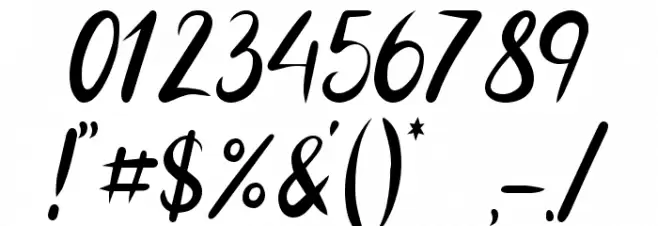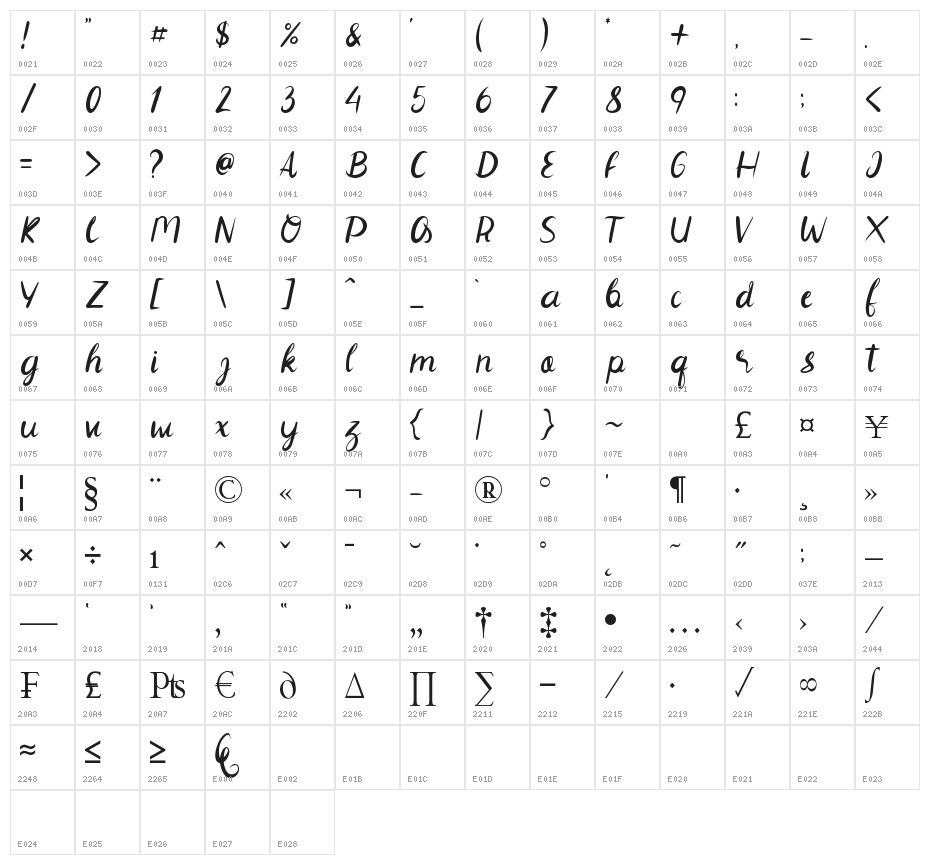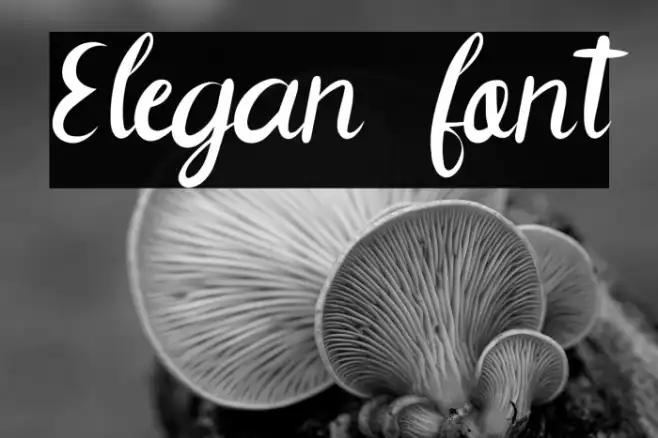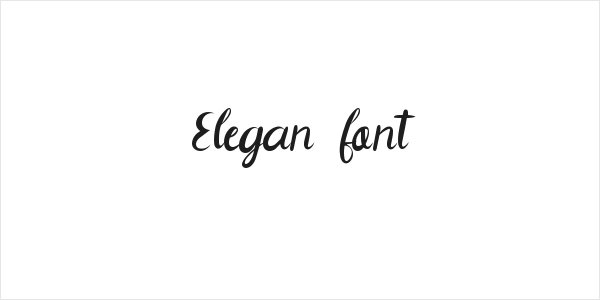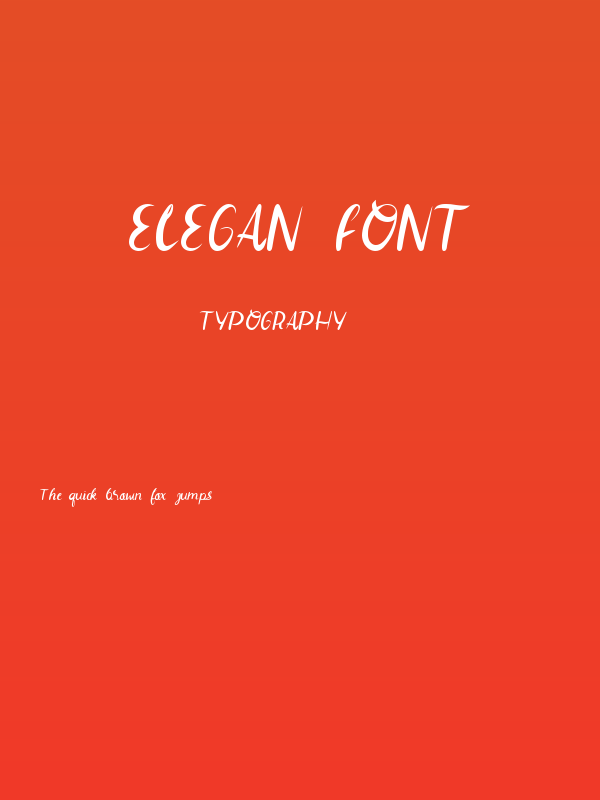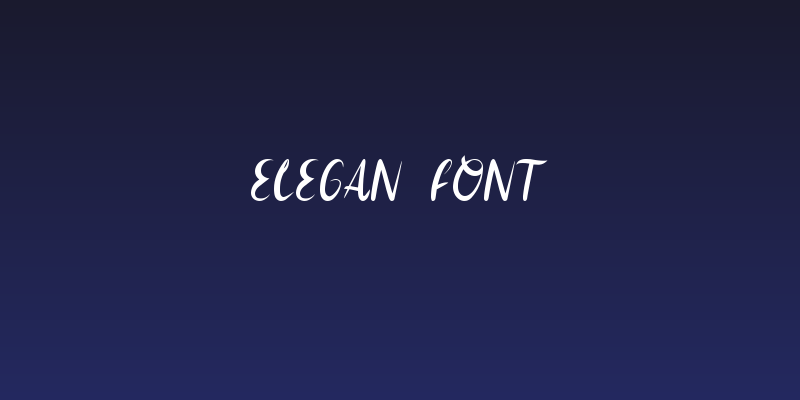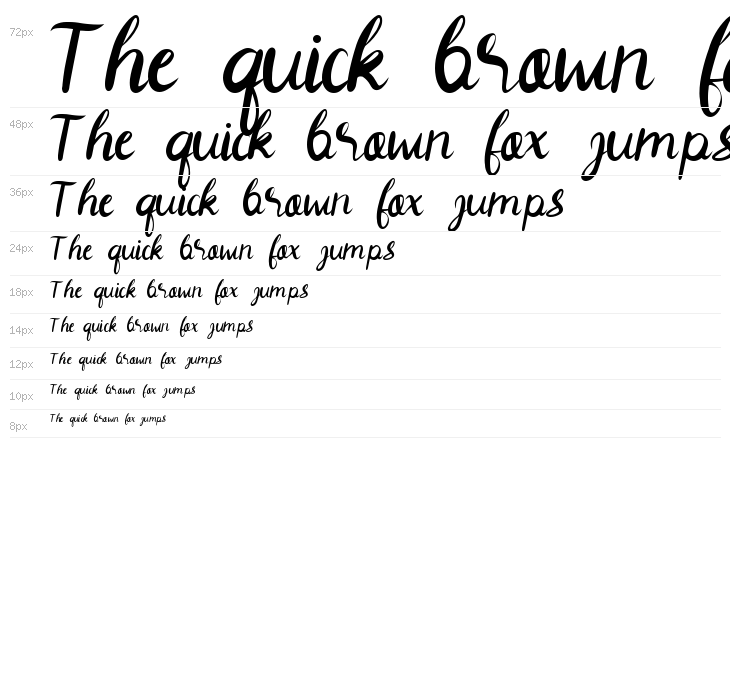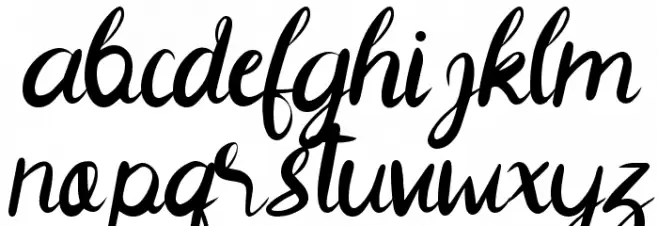
Elegan font Font
| Gesamtstil | Elegant, Handwritten |
| Anwendungsfall | Logos, Invitations, Personal Branding |
| Vorgeschlagene Projekte | Ideal for wedding invitations, greeting cards, personal branding, and elegant logos. |